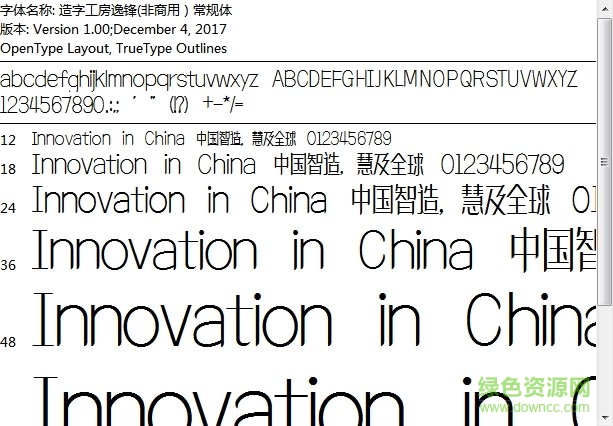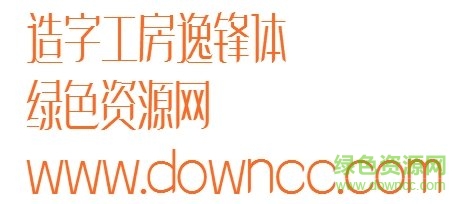
造字工房逸鋒體是一款字形扁長(zhǎng)、簡(jiǎn)潔體面的藝術(shù)字體,結(jié)構(gòu)上的纖細(xì)瘦長(zhǎng)設(shè)計(jì)讓人更能新生好感,字跡更加端正好看,快來綠色資源網(wǎng)試試吧!
造字工房逸鋒體,其字瘦長(zhǎng),筆觸秀麗頎長(zhǎng),圓潤(rùn)順暢,轉(zhuǎn)折處快捷瘦勁,輕重頓挫、富有變化,風(fēng)格柔麗知性,又不失剛韌,此款字體適用于時(shí)尚行業(yè),主作標(biāo)題與副標(biāo)題之用。